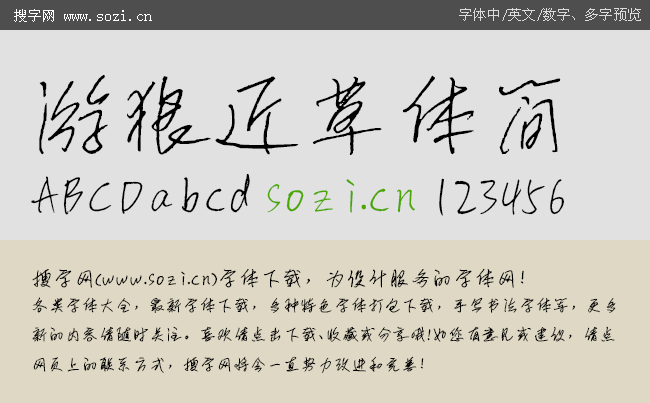
游狼近草體簡
搜字網(wǎng)提供一款游狼近草體簡中文書法字體下載,游狼近草體簡是一款手寫風(fēng)格的書法字體,字體書寫流暢,字形大方,整體效果十分出色,適合應(yīng)用于廣告設(shè)計(jì)、名片設(shè)計(jì)、包裝印刷、兒童產(chǎn)品設(shè)計(jì)等應(yīng)用。